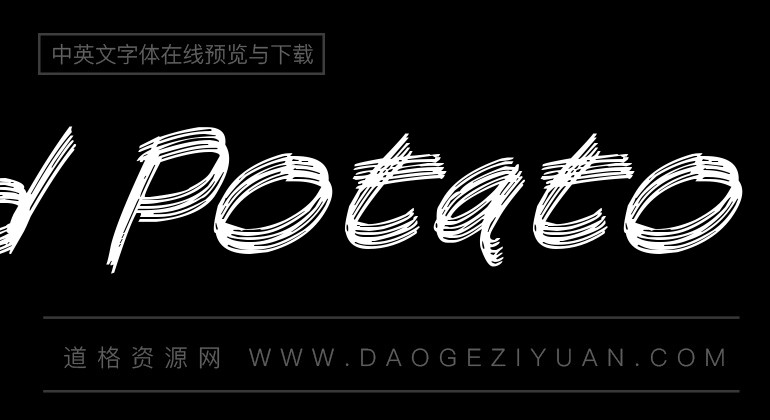
Mad Potato Bill 是一款古老的手写体字体,它的设计灵感来源于18世纪的美国西部乡村文化,具有独特的古朴气息。Mad Potato Bill 字体具有温暖的质感,拥有清晰的细节,它可以用于商业广告,书籍,海报,海报,卡片,T恤,标志和其他印刷品。它让您的设计充满活力,让您的工作变得更加有趣,让你的作品更加具有记忆力。内容介绍
Mad Potato Bill是一款非常不错的手写艺术字体,具有很好的视觉感,适合于文化类的宣传设计、商业类品牌的广告和产品包装设计以及个性化文字排版等较多场景。